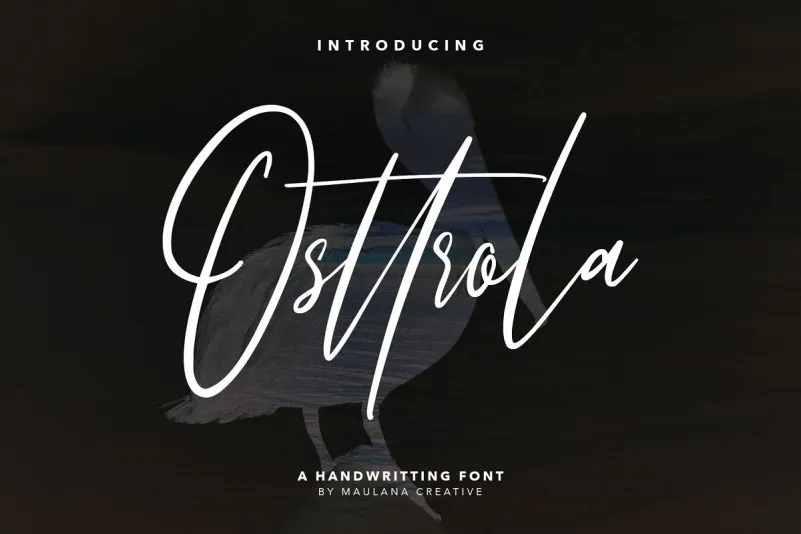
Osttrola Handwritting Font – Download Grátis
A fonte ‘Osttrola Handwriting Font’ é uma opção excepcional para designers que buscam uma mão escrita moderna e elegante. Ela se destaca por seu estilo casual, combinando um toque sofisticado com a leveza da autenticidade à mão. Ideal tanto para aplicativos como marcações ou cartões de casamento quanto para trabalhos mais elaborados como editoriais de revistas ou capas de livros. Osttrola Handwriting é perfeitamente adequada para fins específicos como assinaturas, embalagens de papelaria, logotipos, desenhos tipográficos e citações. Além disso, sua elegância se adapta perfeitamente a design web, cabeçalhos de fliers, etiquetas para roupas e até mesmo a criação de elementos de marca ou pacotes de embalagens. Para aqueles que querem transmitir uma sensação autêntica e atemporal em seus projetos, Osttrola Handwriting é o desejado complemento adicional à sua paleta de recursos gráficos.